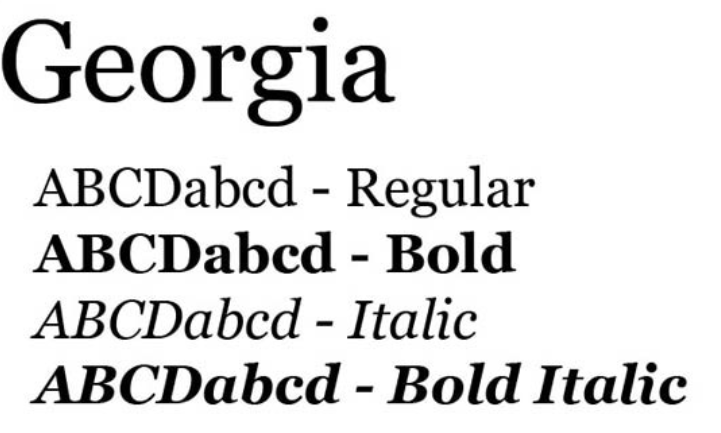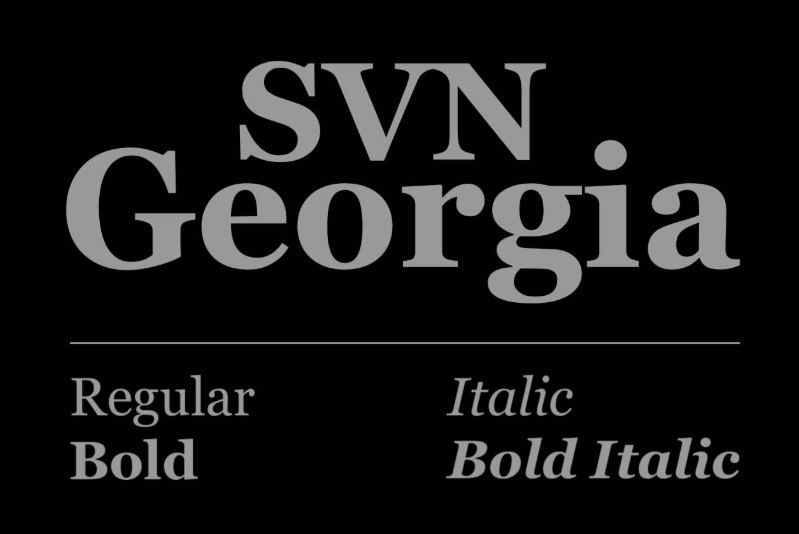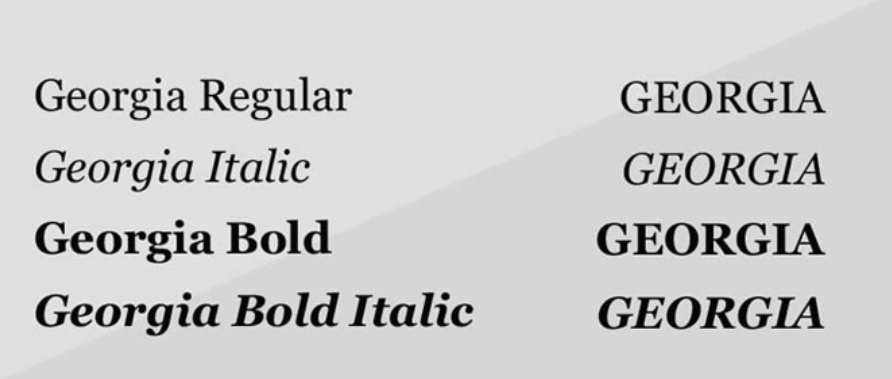
Georgia Font Việt hóa – Tải font chữ có chân cổ điển, thanh lịch và chuyên nghiệp
Font Georgia Việt hóa là bộ phông chữ có chân (Serif) kinh điển được thiết kế bởi Matthew Carter cho Microsoft vào năm 1993, nổi tiếng với khả năng hiển thị cực kỳ rõ nét và dễ đọc ngay cả trên những màn hình độ phân giải thấp. Với cấu trúc chân chữ dày dặn, các đường cong mở rộng và tỷ lệ x-height lớn, Georgia đã trở thành tiêu chuẩn vàng cho các thiết kế sách báo, văn bản trang trọng và bao bì sản phẩm cần độ uy tín cao. Doozypack.vn cung cấp link tải Font Georgia Việt hóa chuẩn kỹ thuật, giúp bạn sở hữu trọn bộ phông chữ cổ điển này, hỗ trợ tiếng Việt đầy đủ để tự tin thiết kế bao bì và bộ nhận diện thương hiệu chuyên nghiệp.
Đặc điểm thẩm mỹ độc đáo của bộ font Georgia
Georgia không đi theo sự mảnh mai của các dòng Serif thời trang; sức mạnh của nó nằm ở tính thực dụng, sự vững chãi và độ dễ đọc vượt trội trong mọi hoàn cảnh hiển thị.
Mẫu chữ Georgia thanh lịch
Phong cách Transitional Serif tối ưu hóa cho khả năng đọc hiểu
Đặc trưng lớn nhất của Font Georgia Việt hóa là cấu trúc chân chữ (serif) có chiều ngang dày dặn và chắc chắn, kết hợp cùng các đường nét chuyển tiếp mượt mà. Khác với các phông chữ truyền thống thường bị mờ nhòe ở kích thước nhỏ, Georgia được thiết kế với các khoảng hở trong chữ (counter) rộng rãi và các đường nét được tối ưu hóa cho điểm ảnh, giúp mắt người nhận diện ký tự một cách nhanh chóng và chính xác nhất.
Cấu trúc chữ vững chãi và x-height lớn vượt trội
Các ký tự của Font Georgia Việt hóa đẹp sở hữu chiều cao chữ cái thường (x-height) lớn hơn đáng kể so với các dòng Serif cùng thời như Times New Roman. Đặc điểm này mang lại cảm giác thân thiện, đĩnh đạc và vô cùng minh bạch. Khi đặt Georgia làm tiêu đề hoặc nội dung mô tả trên bao bì, sản phẩm của bạn sẽ ngay lập tức toát lên vẻ uy tín, chuyên nghiệp và tạo dựng niềm tin vững chắc với người tiêu dùng.
Ưu điểm nổi bật của bản Font Georgia Việt hóa đẹp
Khi ứng dụng các phông chữ kinh điển vào thị trường trong nước, sự chỉn chu về dấu câu là yếu tố quyết định đến tính chuyên nghiệp của ấn phẩm:
• Khắc phục triệt để lỗi dấu tiếng Việt: Phiên bản Việt hóa đã được đội ngũ thiết kế trau chuốt thủ công từng dấu câu. Các dấu sắc, huyền, hỏi, ngã, nặng được vẽ với tỷ lệ cân đối, đặt ở vị trí thoáng đãng so với thân chữ, không gây cảm giác chắp vá hay đè nét làm mất tính thẩm mỹ.
• Bảo đảm tính đồng nhất thương hiệu: Việc sử dụng bản font chuẩn giúp bạn tự tin dàn trang tiêu đề tiếng Việt mà không lo hiện tượng lỗi ô vuông hay nhảy về font hệ thống khô khan.
Kiểu chữ serif dễ đọc
Biến thể Font Đặc điểm thị giác Ứng dụng đề xuất tại Doozypack.vn
Georgia Regular Cân đối, thông thoáng, dễ đọc Dùng cho nội dung hướng dẫn sử dụng, bảng thành phần (Body text).
Georgia Bold Dày dặn, vững chãi, nổi bật Dùng làm tiêu đề chính, tên sản phẩm hoặc logo thương hiệu.
Georgia Italic Nghiêng nhẹ, tinh tế, cổ điển Dùng cho các trích dẫn ngắn, ghi chú hoặc lời cảm ơn trên vỏ hộp.
• Bao bì Trà thảo mộc & Cà phê di sản: Nét chữ Serif cổ điển kết hợp hoàn hảo cùng chất liệu giấy Kraft nâu thô mộc, tạo nên phong cách mộc mạc, uy tín và đậm đà phong vị gia truyền.
• Hộp giấy đựng Dược phẩm & Thực phẩm chức năng: Thông tin liều lượng, thành phần in bằng font Georgia giúp người dùng dễ dàng tra cứu, tạo niềm tin tuyệt đối về tính minh bạch của sản phẩm.
• Hộp quà tặng doanh nghiệp & Kỷ niệm thành lập: Nét chữ đĩnh đạc giúp các ấn phẩm quà tặng toát lên vẻ lịch lãm, chuyên nghiệp và khẳng định vị thế uy tín bền vững.
Thiết kế typography cổ điển
03 Lưu ý kỹ thuật khi in ấn với phông chữ có chân Georgia
Việc sản xuất bao bì thực tế sử dụng các phông chữ tiêu chuẩn đòi hỏi sự am hiểu kỹ thuật chuyên sâu tại xưởng in Doozypack.vn:
• Kiểm soát kích thước chữ tối thiểu: Trên chất liệu giấy Ivory nhẵn mịn, chữ Georgia hiển thị rất rõ ràng ở kích thước 5pt. Tuy nhiên, trên giấy Kraft thô nhám, bạn nên để size chữ tối thiểu từ 7pt trở lên để thớ giấy không làm mờ các chi tiết chân chữ.